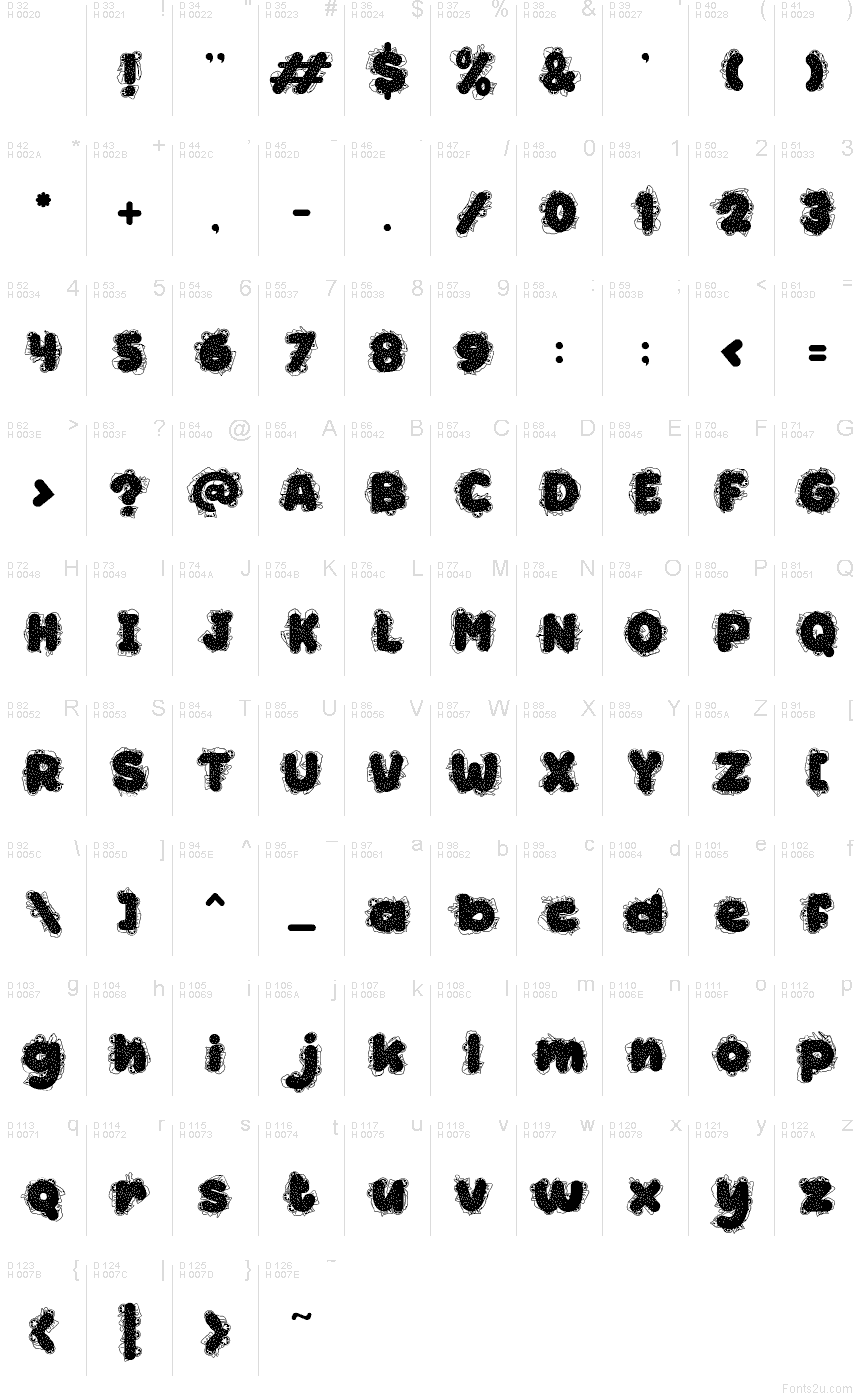
Smoky Maple Two de Putracetol Studio es una fuente display gratuita de estilo graffiti-bubble, con una estética de pegatina y trazado a mano. Las letras se ven infladas y densamente garabateadas, mientras que los contornos sueltos, las pequeñas firmas y las formas superpuestas le dan un aire de arte con rotulador, como si estuviera plasmada en la portada de un cuaderno o en un póster callejero.
Encaja muy bien en flyers musicales, gráficas de eventos juveniles, portadas de zines, packaging para marcas divertidas y posts en redes sociales que necesitan un titular llamativo. Esta fuente gratuita también funciona de maravilla para títulos o diseños breves de merchandising. Debido a que sus formas son gruesas y cargadas, se siente más cómoda en palabras cortas donde esa textura de garabato pueda destacar.